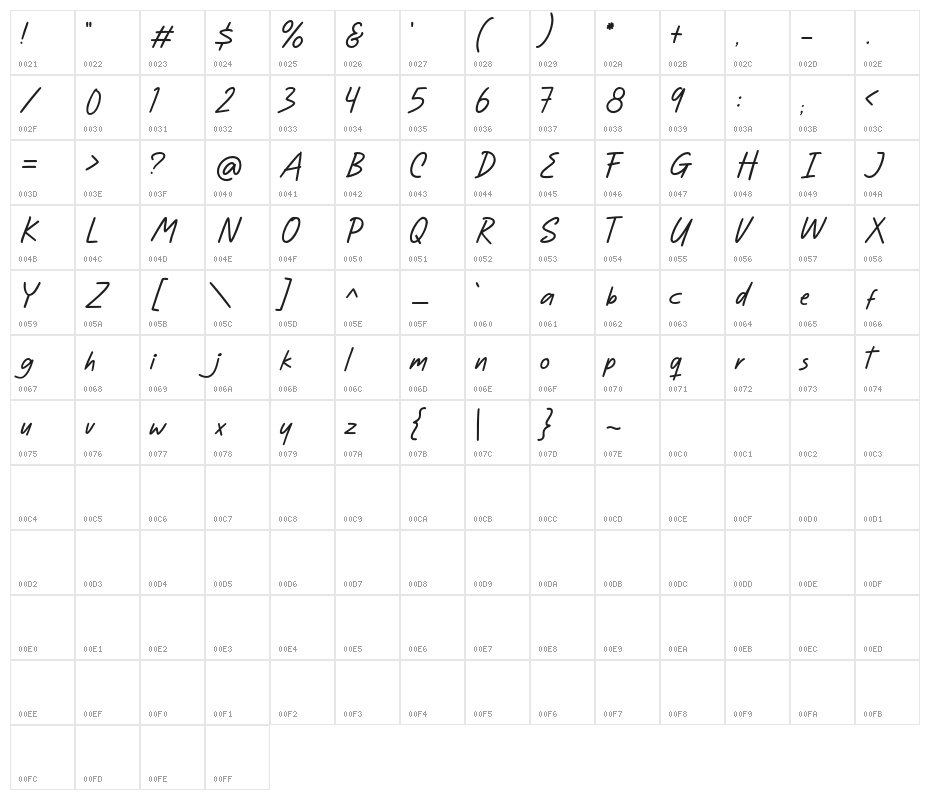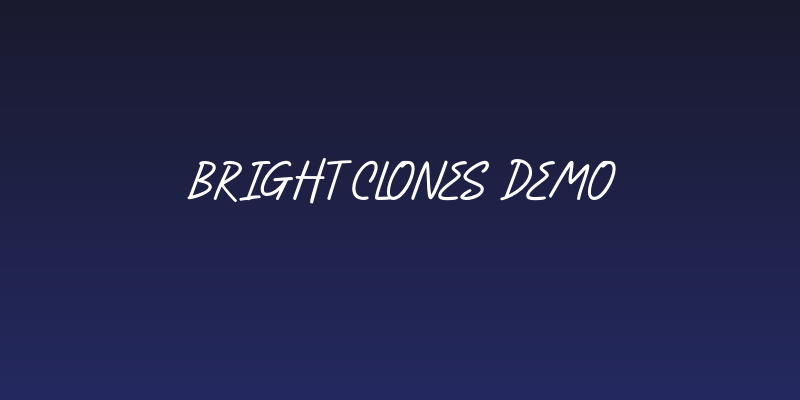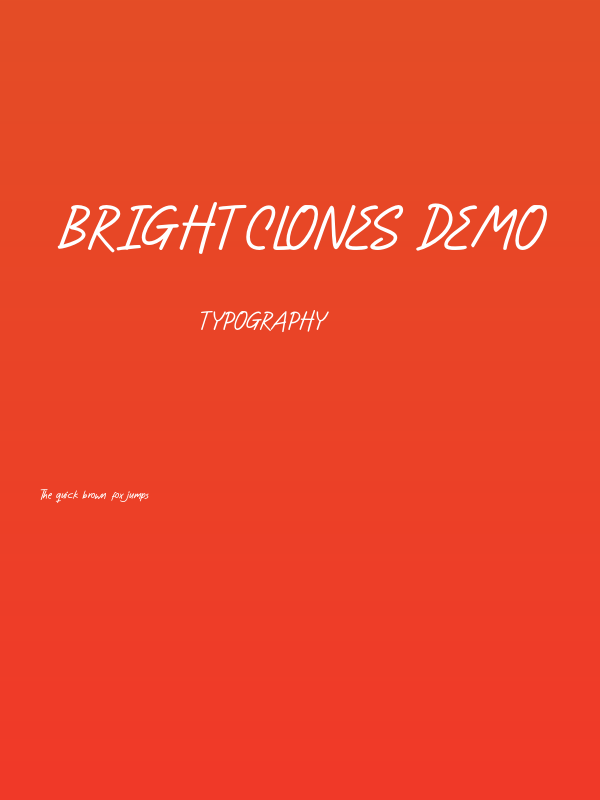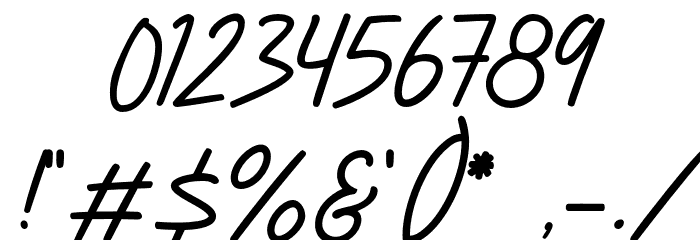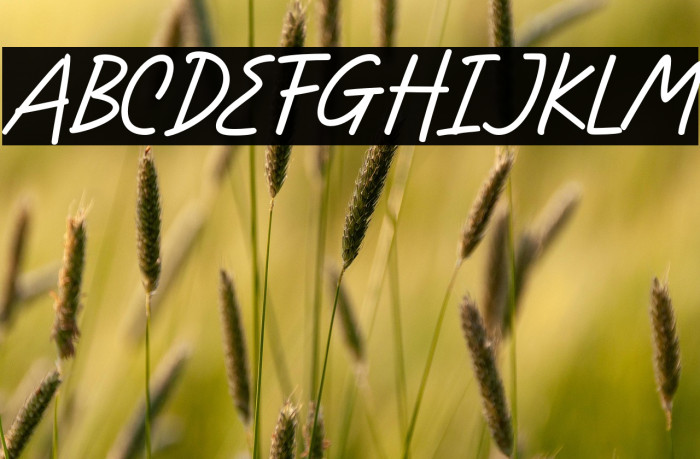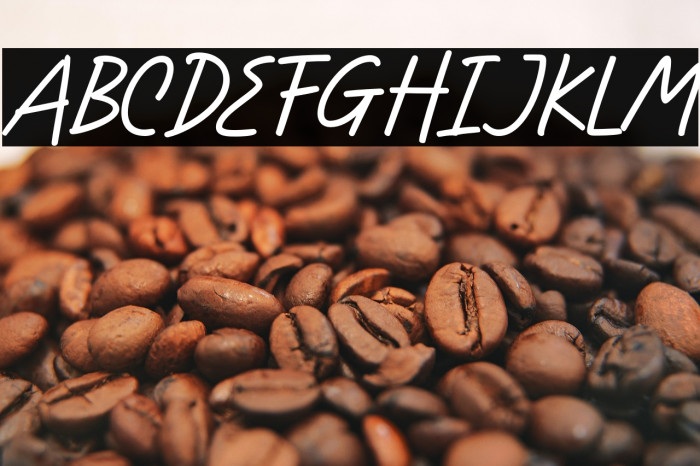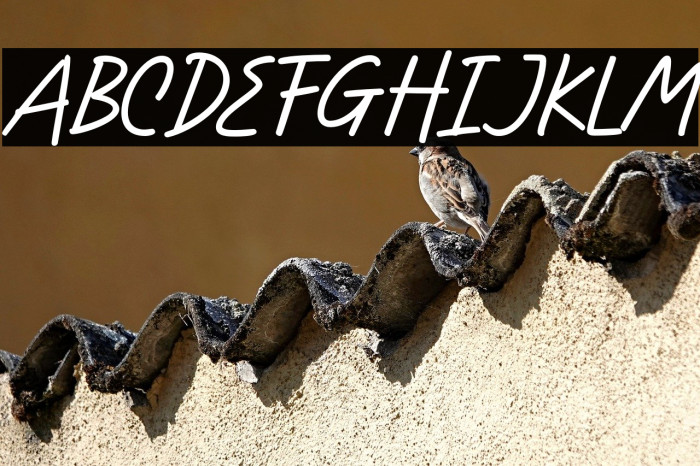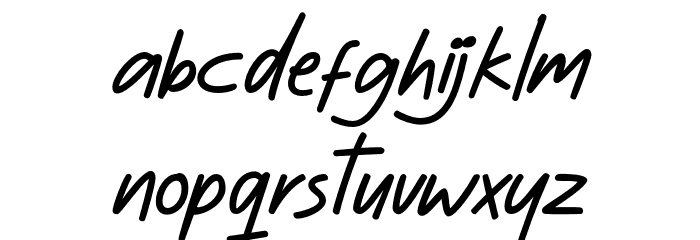
Bright Clones DEMO Font
| Estilo general | Casual, Playful |
| Caso de uso | Headlines, Logos, Invitations |
| Proyectos propuestos | Ideal for greeting cards, invitations, personal branding, and creative projects that require a personal touch. |